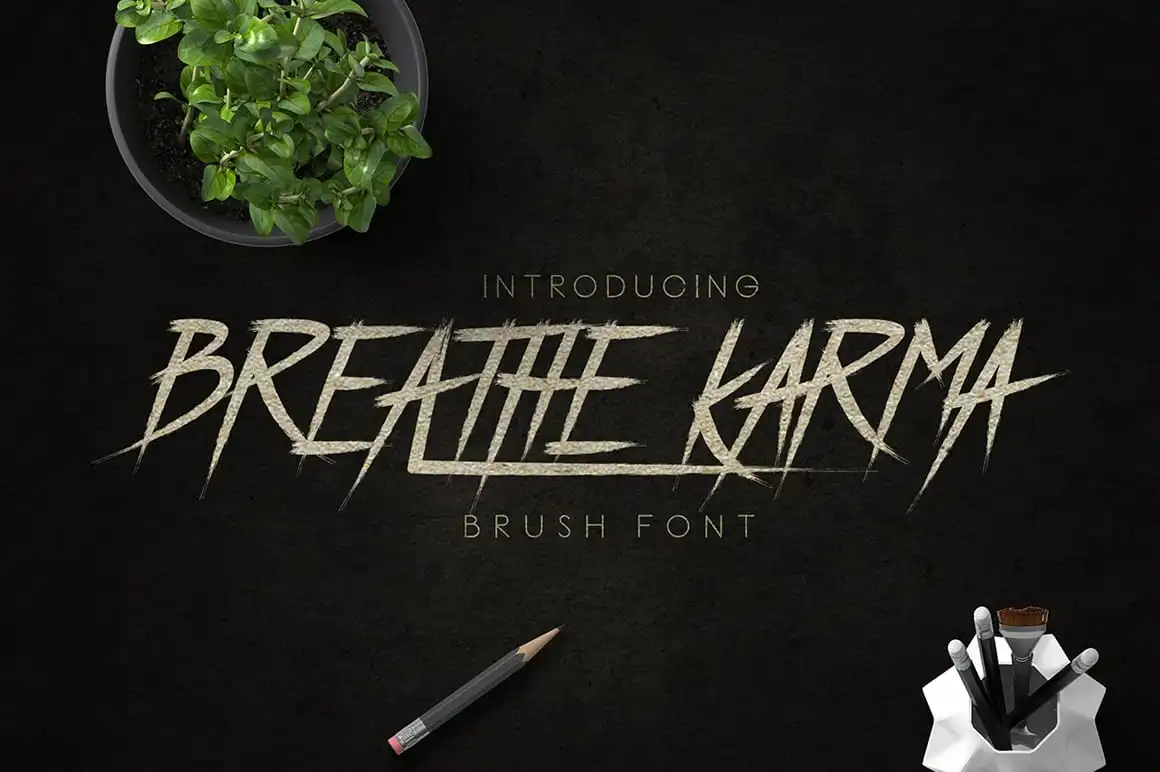
Breathe Karma Typeface – Download Grátis
A Breathe Karma Typeface é uma fonte tipográfica inspirada nas antigas e estilos antigos, criando um estilo vintage e único. Este design elegante é perfeito para criar rótulos de produtos ou embalagens, cartões de convite, camisetas e até mesmo a posteridades. Esta fonte está disponível como versão gratuita, o que torna o design fácil e acessível para qualquer pessoa. Se você deseja experimentar a sua versão completa, basta clicar no link abaixo e visitar meu estúdio para explorar mais nossas excelentes fontes.